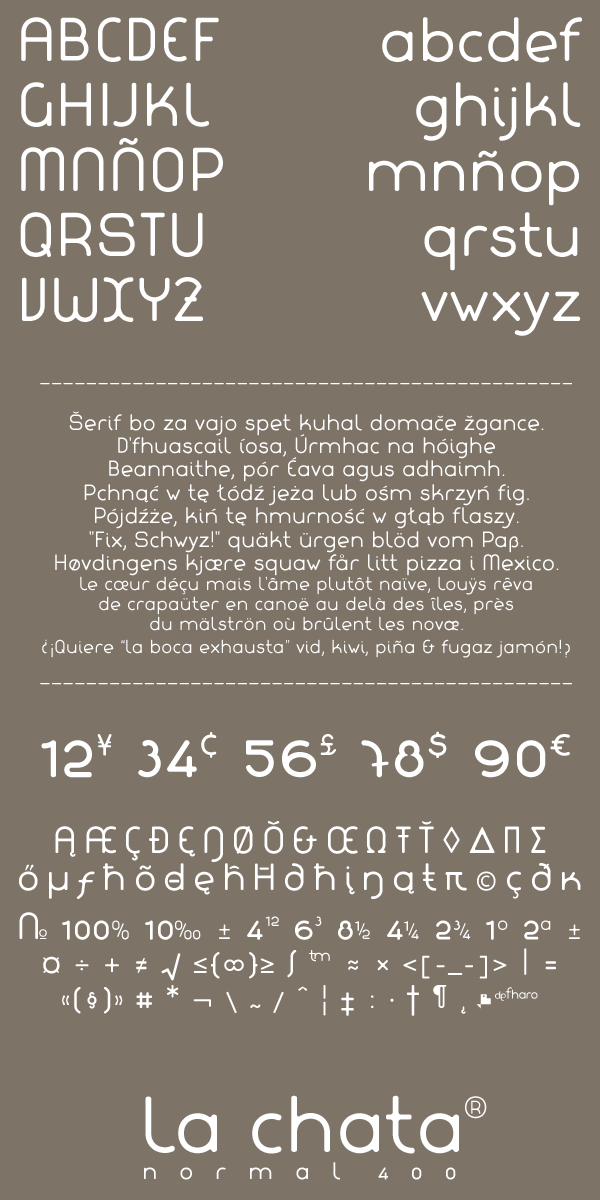
Font name: | La chata |
Esta es una tipografía de palo seco, uniforme, con acabado redondeado en las terminaciones de las astas, ápices, vértices, colas o espolones, también en las uniones con el asta de los travesaños, barras y hombros. Funciona bien en la web a partir de 11pt. Disponible en varios formatos, incluyendo webfonts. Commercial license: http://defharo.com/fonts/la-chata-a-free-web-font/ |